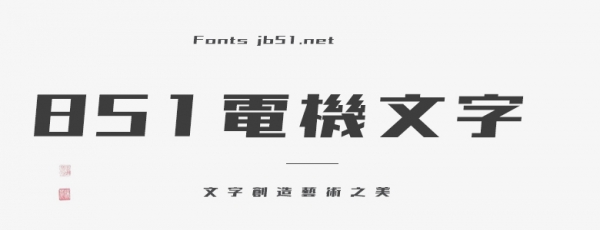
851電機(jī)文字體是一款充滿(mǎn)銳利感的剛性字體,跟我們國(guó)內(nèi)的站酷高端黑的風(fēng)格相類(lèi)似,但是它有一定傾斜角度,看上去更有速度感。豎畫(huà)傾斜5°,字體文件格式為T(mén)TF,同時(shí)提供免費(fèi)在線預(yù)覽,免費(fèi)在線轉(zhuǎn)換以及免費(fèi)下載。